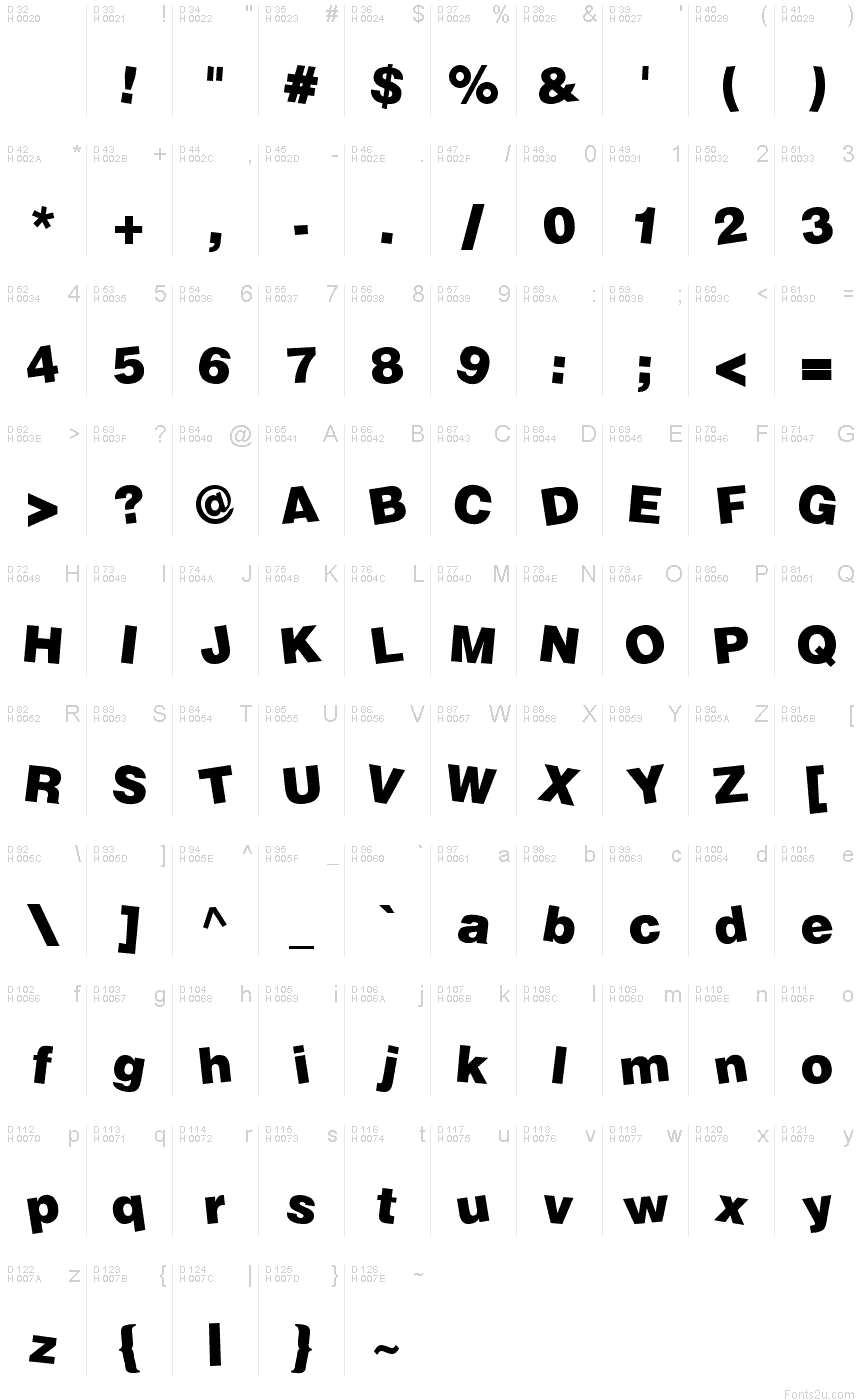
Soopafresh
Soopafresh — это бесплатный комиксный шрифт от Класа Калларссона, крупный и «резиновый» привет из 90-х с улыбкой до ушей. Буквы выглядят надутыми и слегка разбалансированными, с тяжелыми округлыми формами и игривым наклоном вперед, что придает надписям динамику, а не академическую строгость.
Шрифт отлично подходит для оформления скейтбордов, флаеров на детские мероприятия, упаковки сладостей, заголовков журналов и броских названий, где нужно мгновенно добавить мультяшной энергии. Благодаря своим раздутым и неровным формам он также хорош для коротких логотипов или акцентных надписей, которым нужно выглядеть ярко, дружелюбно и намеренно небрежно.